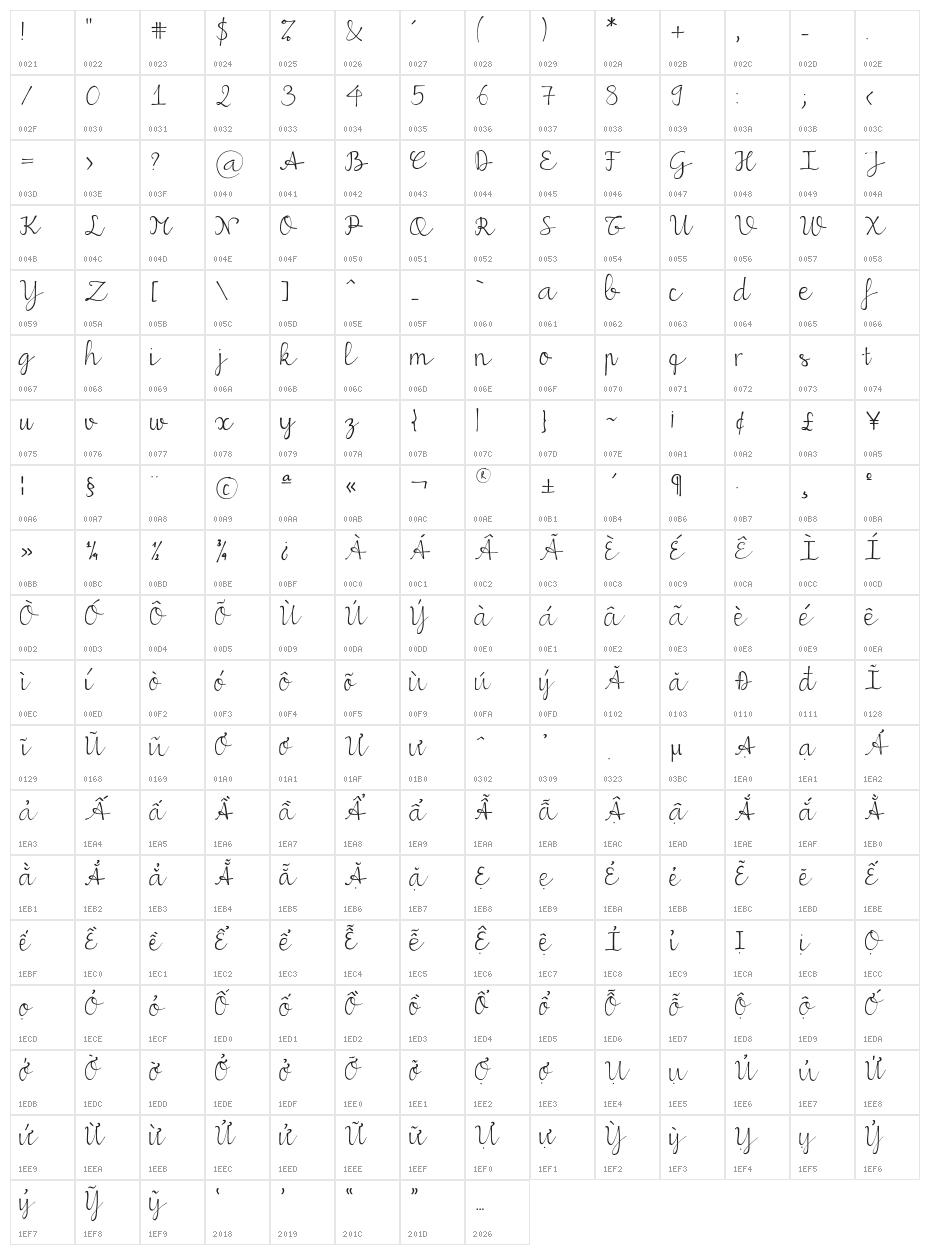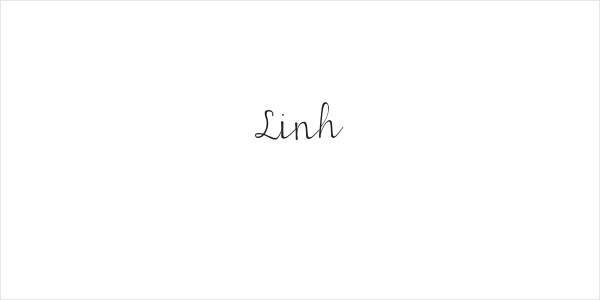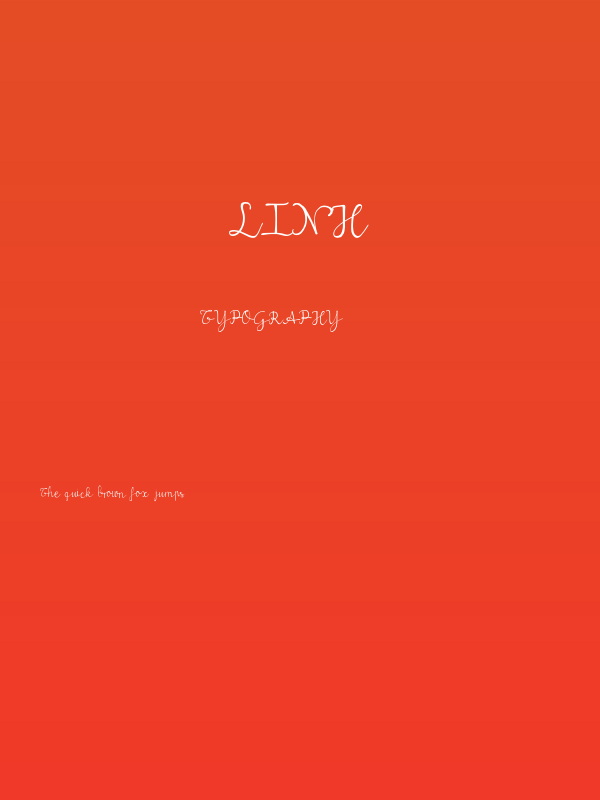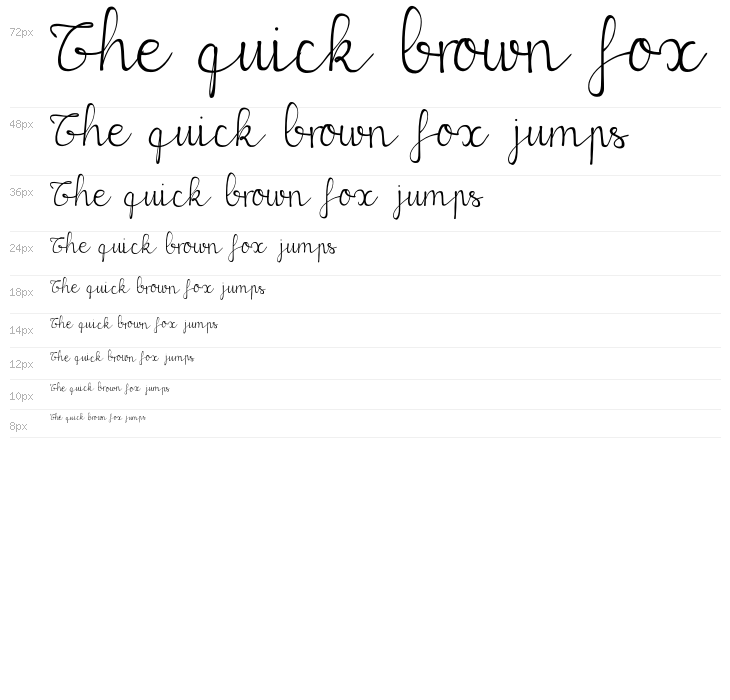
Linh Font
✎ Handwritten
Fonts by Linh Pham Thi Dieu
| 分类 | Handwritten |
| 整体风格 | Casual, Personal |
| 使用场景 | Invitations, Greeting cards, Personal letters |
| 推荐项目 | Ideal for greeting cards, personal letters, invitations, and branding materials that require a personal touch. |